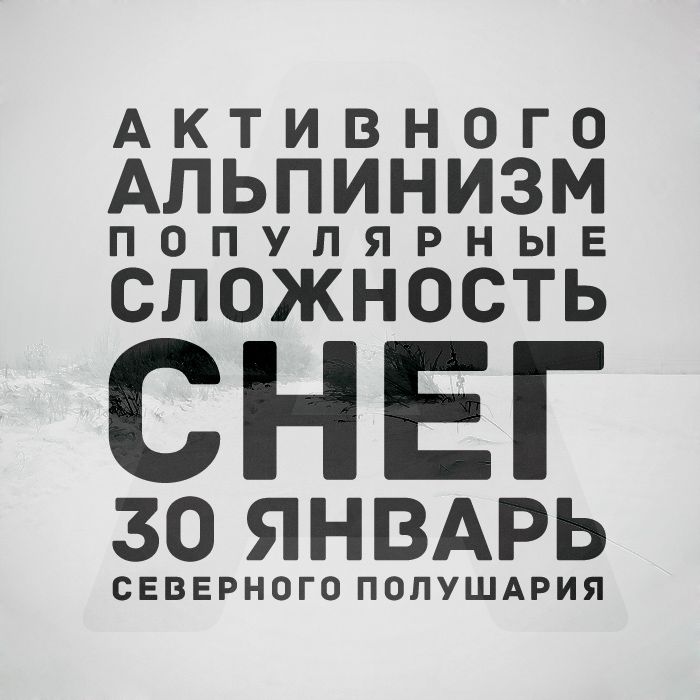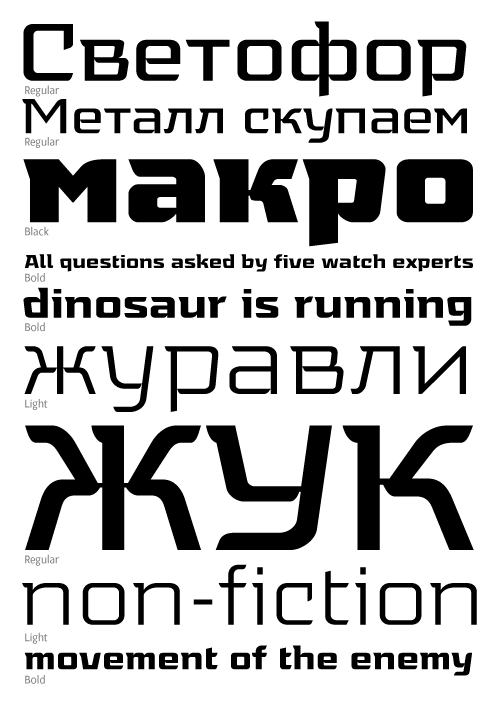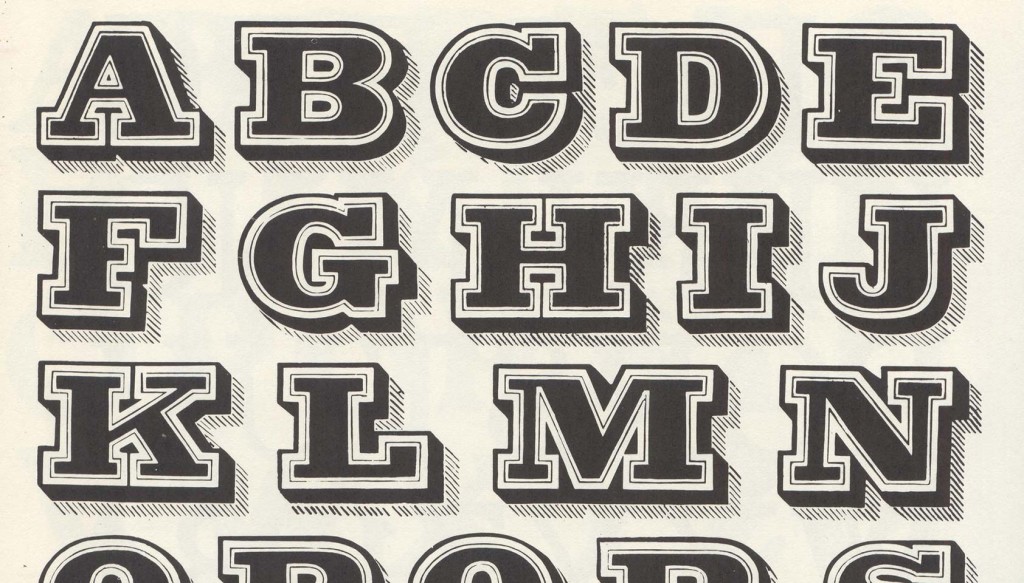
Подсознательные значения выбранных шрифтов — DEADSIGN
Всякий раз, когда люди общаются, в основе высказанных ими слов и невербальных сигналов всегда есть очевидный посыл. В разговоре невербальный контакт происходит посредством взглядов, поз и тона голоса. Эти маленькие, но существенные детали являются чрезвычайно важной частью получаемого в процессе общения сообщения.
В печати или онлайн невербальные сигналы уже другие. В «немых» медиа у нас есть макеты, цвета и изображения, которые сопровождают наши сообщения. И, конечно, есть ещё типографика. Эта часть дизайна трудно уловима, но начертания и стили шрифтов, которые мы применяем, в действительности могут нести в себе подсознательные значения. Дизайнеры могут играть с сублиминальными реакциями человека на различные стили типографики в качестве опоры идеи любого проекта.
Читаемость
Существует множество причудливых шрифтов, которые могут показаться вам заманчивыми. Но если они жертвуют читаемостью, они почти всегда того не стоят.
Люди куда больше предпочитают получать сообщение, которое ясно сформулировано и словами, и начертанием. Это особенно важно, если вы просите людей что-то сделать.
Одно исследование показывает, что в тестовой группе люди легче принимали решение, если сообщение легко читалось. Следуя такой философии, создание призывов к действию (call-to-actions) с использованием хорошо читаемых шрифтов должно подстегнуть большее вовлечение.
Правда в этой статье утверждается, что в некоторых случаях что-то менее доступное для понимания сходу тоже может сработать. Например, если вы хотите, чтобы люди провели больше времени в ресторане. Для многих, если позиции в меню читаются или понимаются тяжело, значит блюда в этом меню также тяжело создаются и, соответственно, стоят дороже.
Пол
Как и многие вещи в мире, даже шрифты могут быть разделены на мужские и женские. Женские шрифты обычно описываются, как тонкие, антиквенные, гладкие и элегантные, а мужские характеризуются, как угловатые и жирные.
Когда вы анализируете различные сборники женских и мужских шрифтов, обнаруживается, что подобные обобщения в значительной степени справедливы.
С помощью этого наблюдения можно эффективно выбирать нужный шрифт под конкретный пол как цель маркетинговой кампании. Сайты или реклама, которые должны привлекать мужчин или женщин, могут заранее продумать используемые шрифты для достижения конечного замысла.
Продукты, предназначенные для женщин, лучше подавать с помощью более элегантных изогнутых шрифтов, в то время как товары для мужчин больше выиграют от применения более жирных и угловатых начертаний.
Хотя в своём большинстве корпоративная типографика склоняется к более мужественным шрифтам, поскольку всем кажется, будто они означают большую организованность и профессионализм. И не удивительно, что женские шрифты типично приносят больше пользы в достижении пафосности.
Здесь, конечно, можно было бы вставить какую-нибудь шутку про гендерные стереотипы, но во избежание жарких дискуссий, я лучше промолчу.
Засечки
Старейший холивар в шрифтовом сообществе касается того, что лучше: антиква или гротеск (недавний редизайн логотипа Google — отличный пример такого холивара). А ведь разница по существу состоит в крошечных штрихах на окончаниях букв. Есть множество теоретических аргументов в пользу обеих точек зрения, но в конечном счёте кажется, будто и нет никаких научных доказательств, которые подтверждают преимущество одного мнения над другим.
Хотя, действительно кажется, что большинство пользователей предпочитает применять антикву на сайтах и в электронной почте, а гротесковые шрифты в деловой документации. Это значит, что Times New Roman по-прежнему останется стандартом для резюме, а Arial будет шрифтом по умолчанию для почты.
Есть ещё много того, чего мы не знаем о начертаниях. Может ли шрифт придать вашей работе больше авторитетности? Возможно, нет никакой существенной разницы между антиквенной Georgia (мой любимый шрифт на все времена) и гротесковой Tahoma.
Но, если копнуть чуть глубже и сравнить солидность Helvetica с, скажем, извечным объектом шрифтовых насмешек, Comic Sans, между ними обнаруживается значительное неравенство.
Грамотный выбор шрифта может создать такое же сильное впечатление, как это делают слова, которыми написан текст. Сайты и бизнес, основанные на креативе и дизайне могут извлечь выгоду из более артистичных шрифтов. А организациям, полагающимся на доверие и надёжность, стоит поискать более структурированные начертания.
Некоторые случаи естественным образом подходят определённым жанрам типографики. В конечном итоге выбор лучшего шрифта для воплощения ваших целей и подходящего вашей сфере сводится к нашим предпочтениям и склонностям. Пока ваши дизайнерские решения читаемы, выполняют своё назначение и соответствуют обстоятельствам, выбор шрифта в целом ничего не испортит.
Помните, что вы не должны заново изобретать колесо, просто нужно научиться использовать уже готовую модель, которая поспособствует вашему прогрессу.